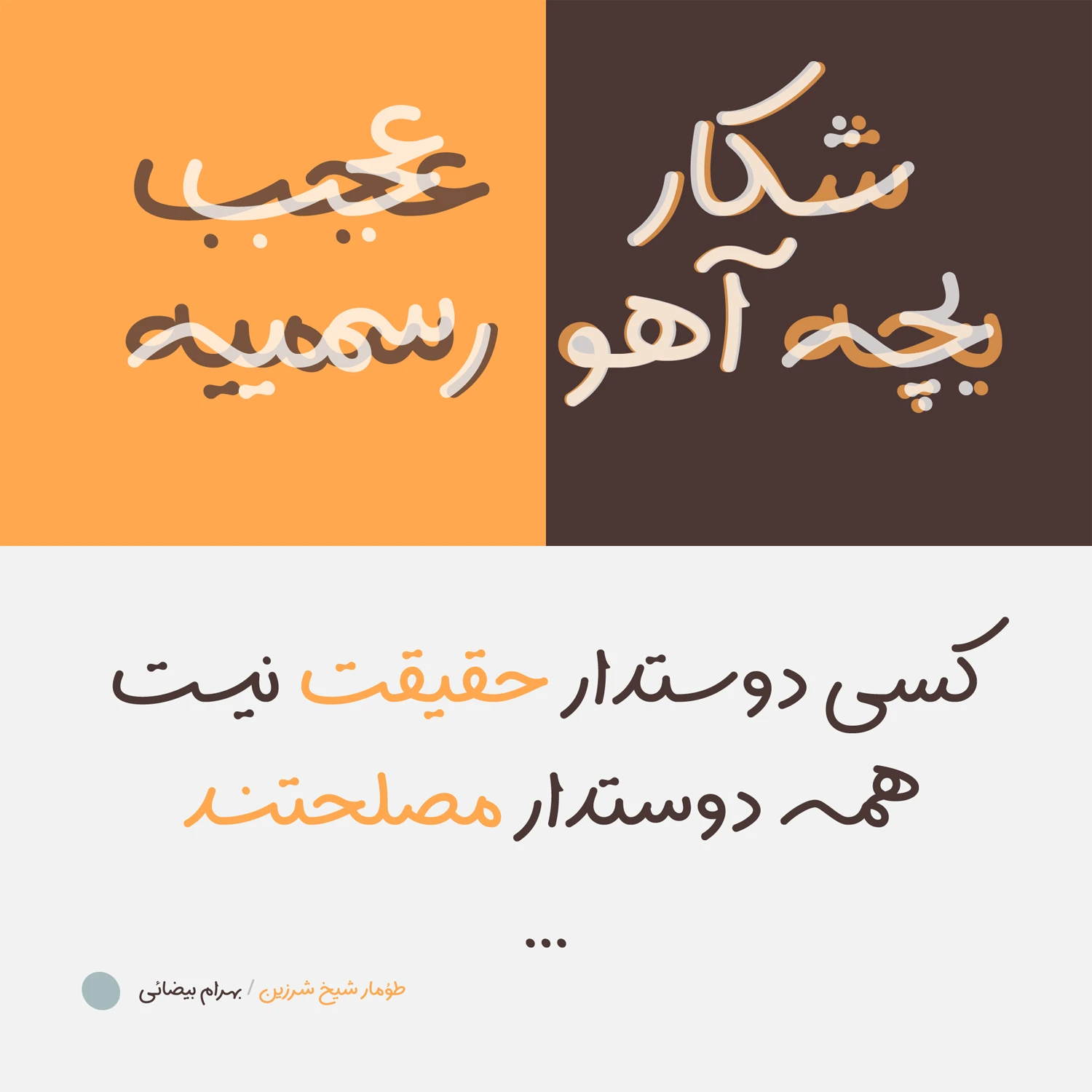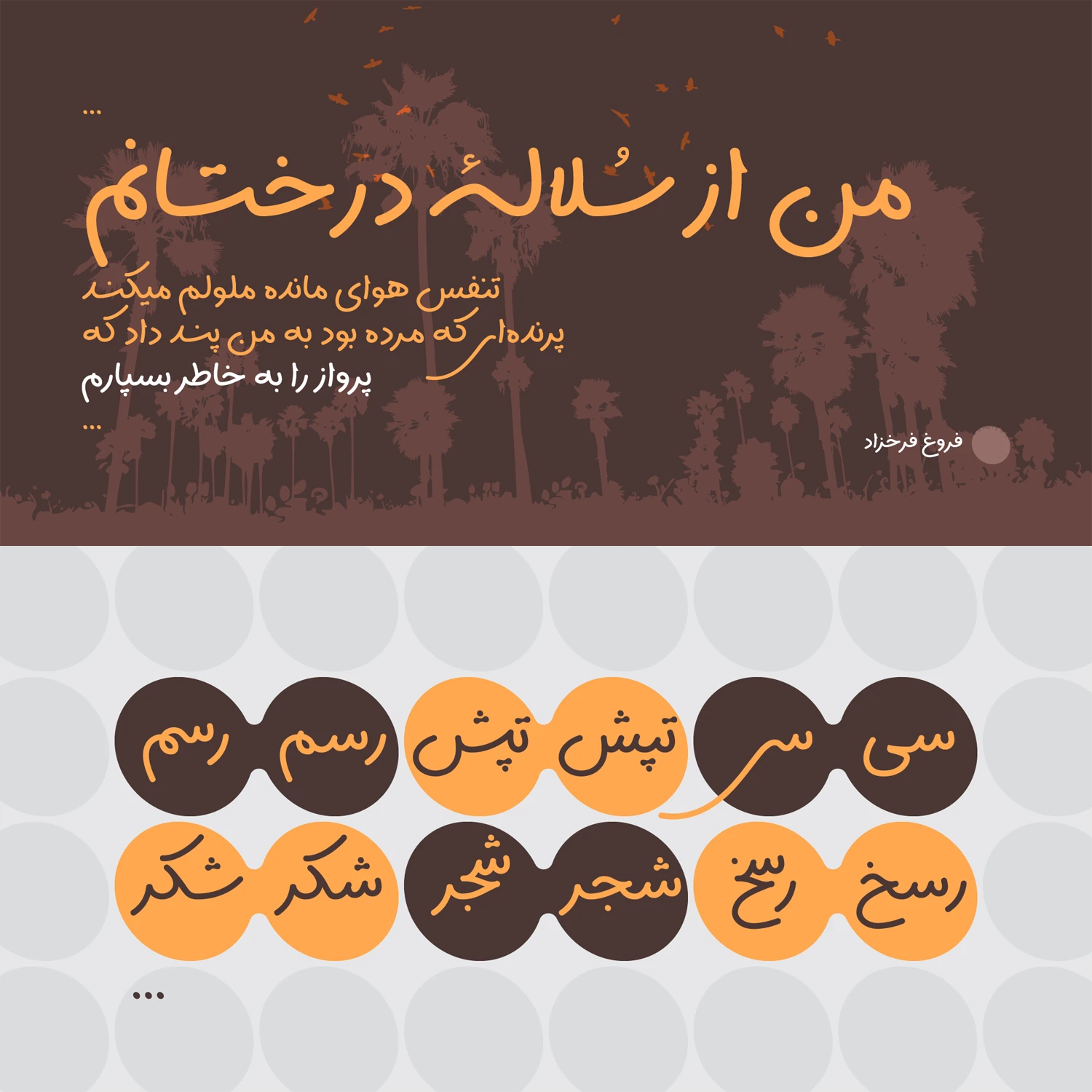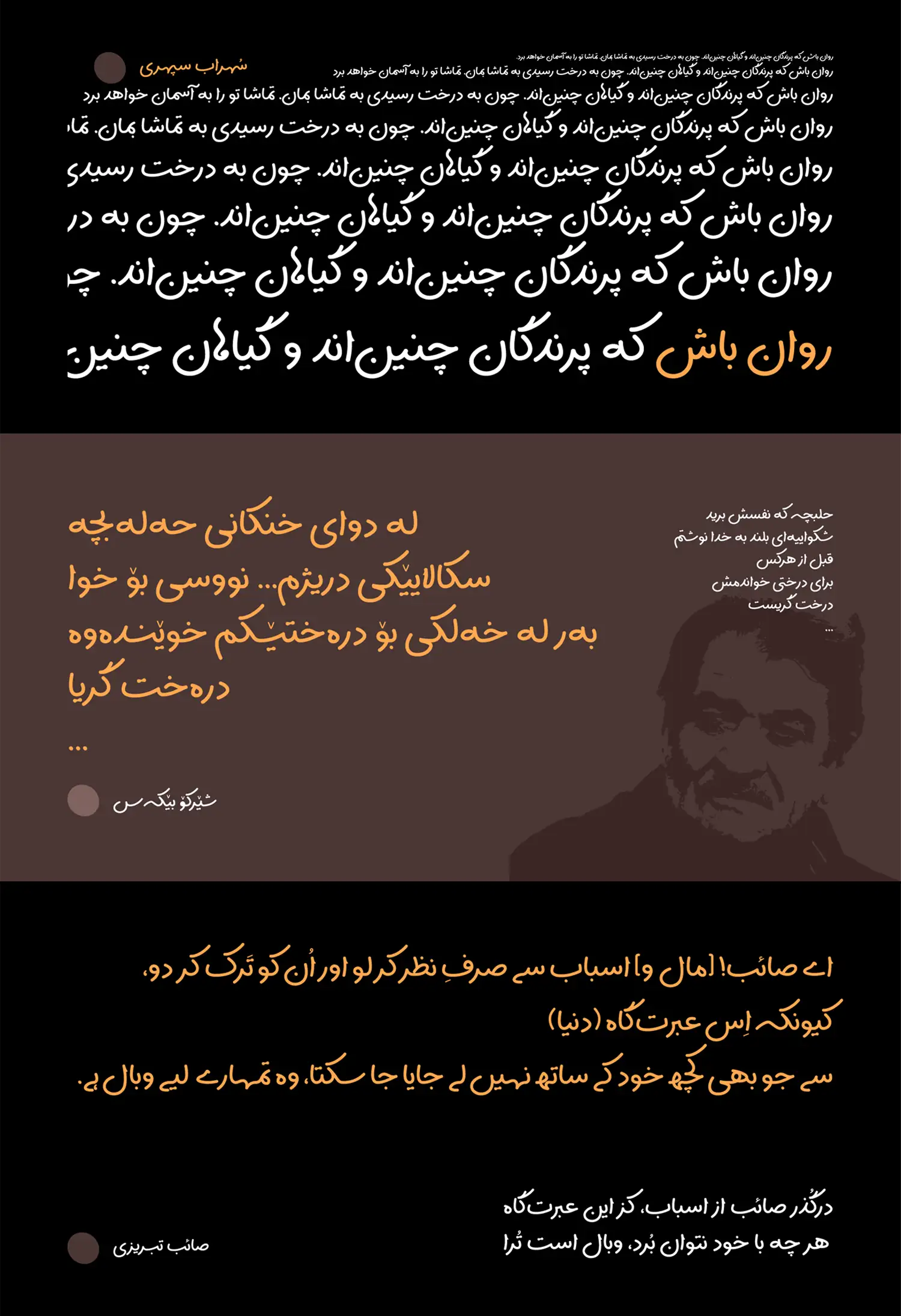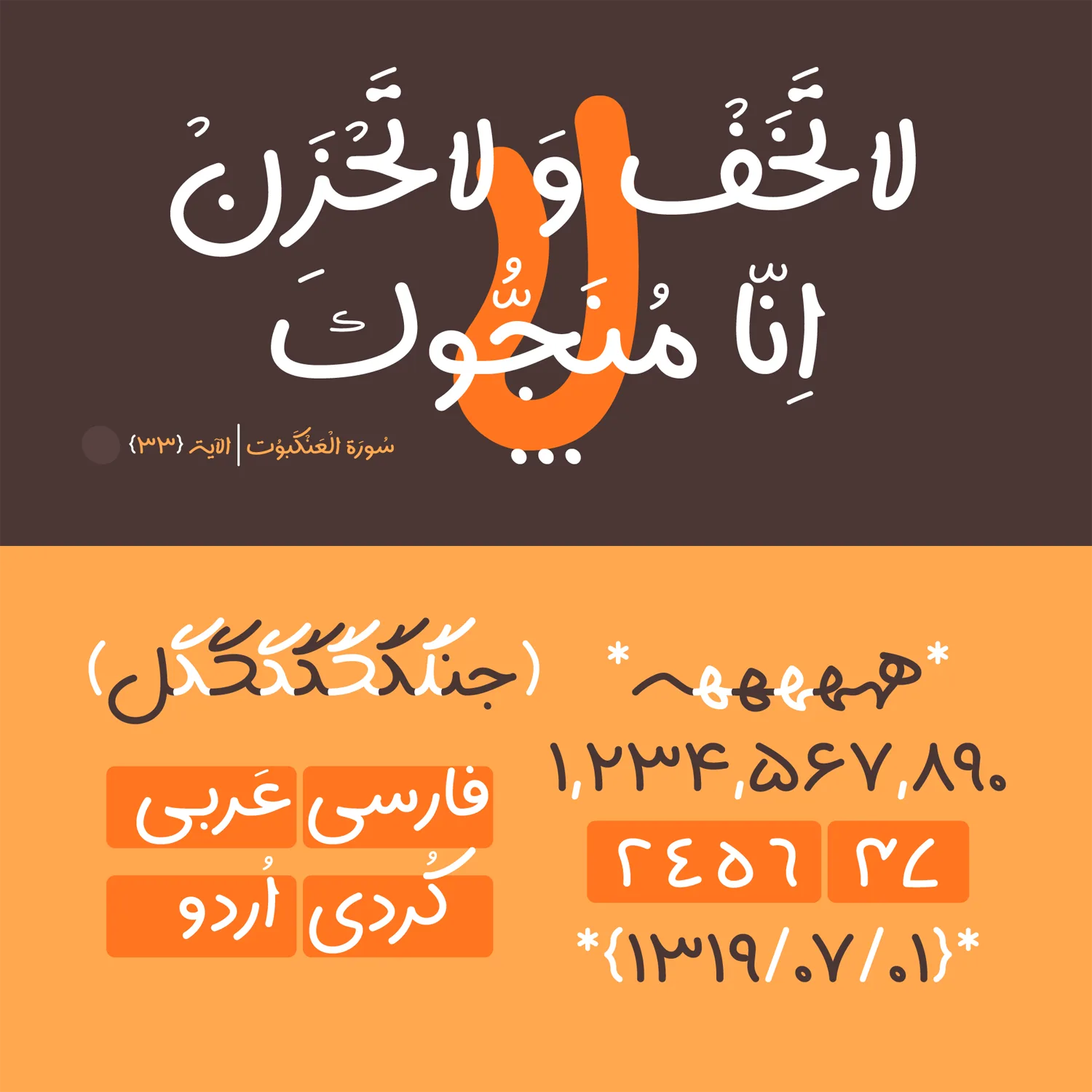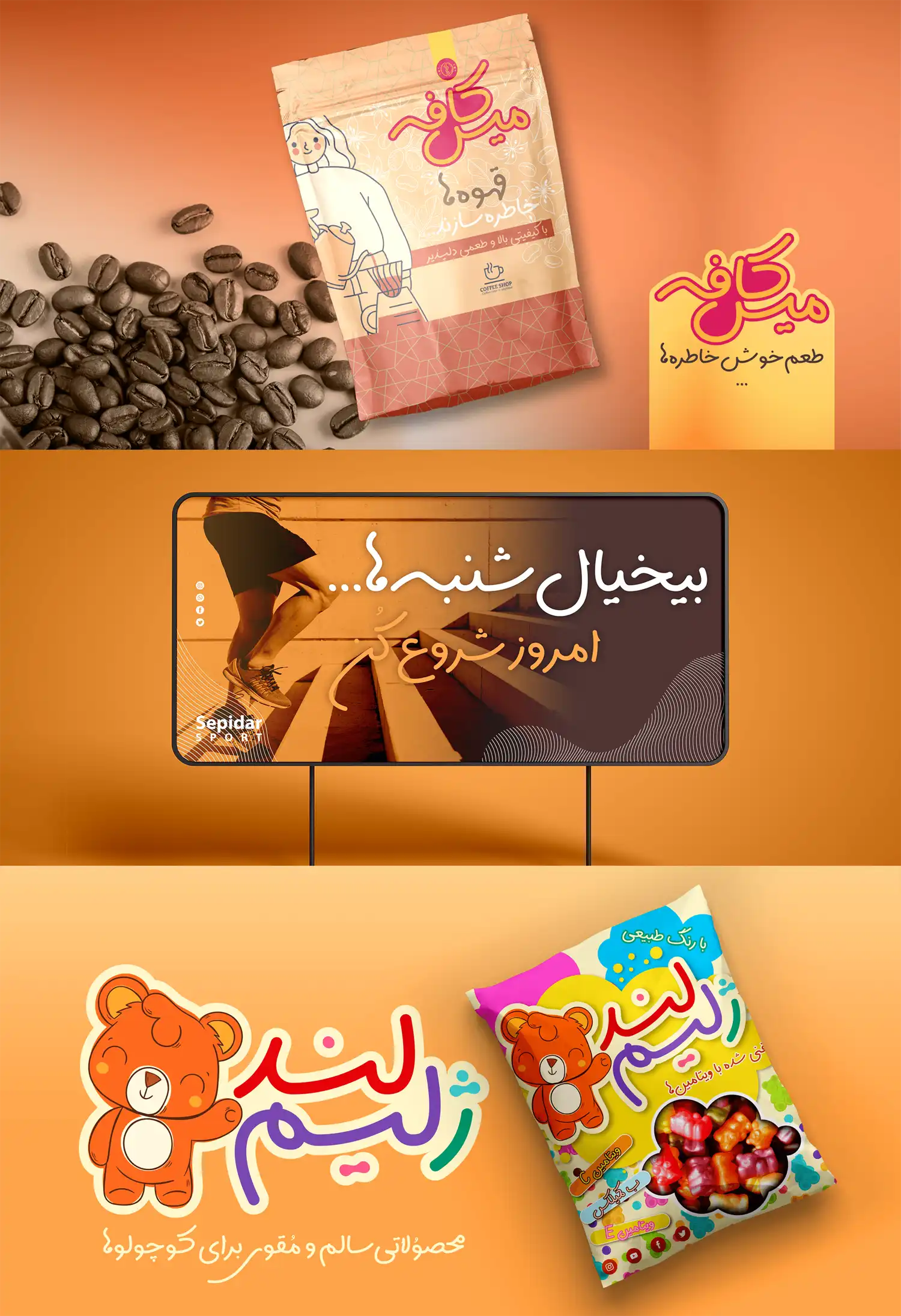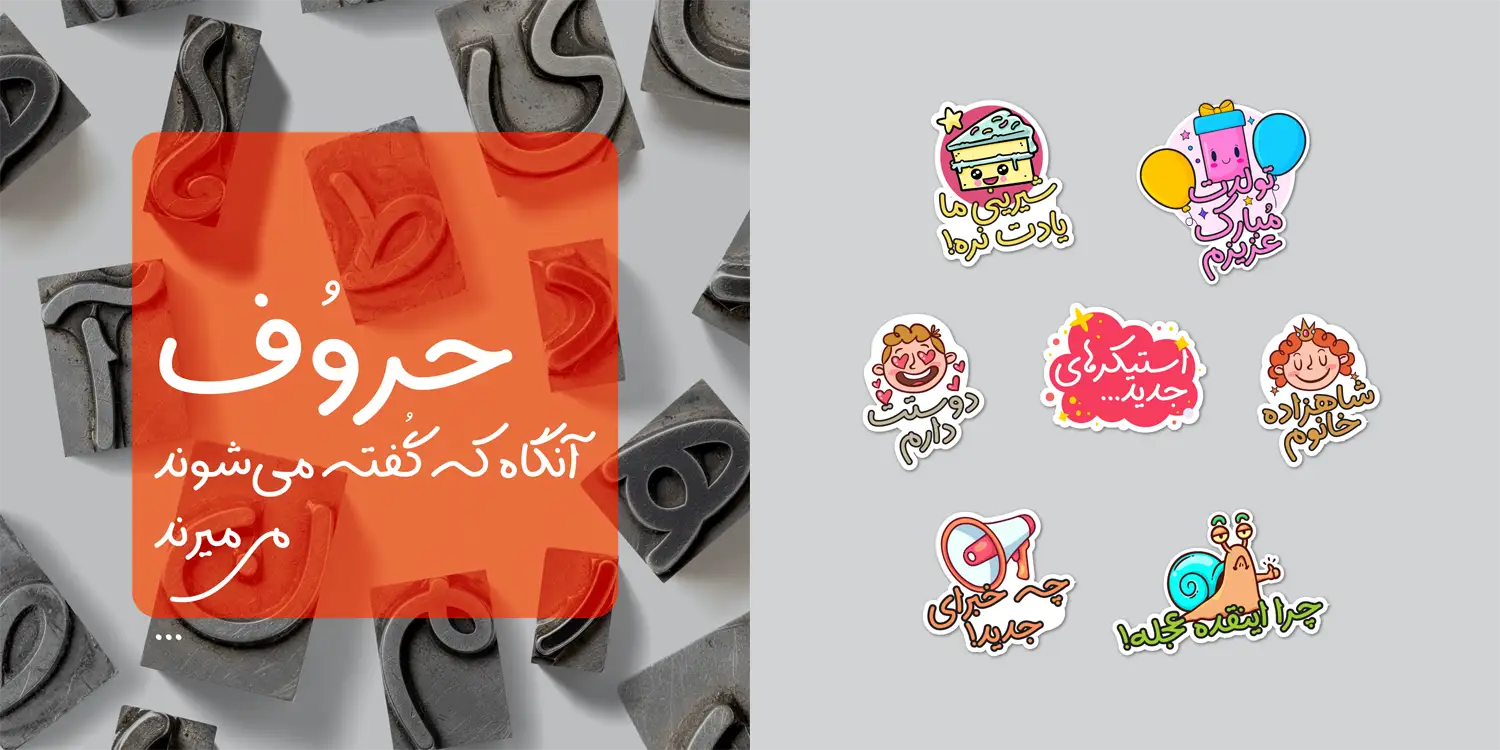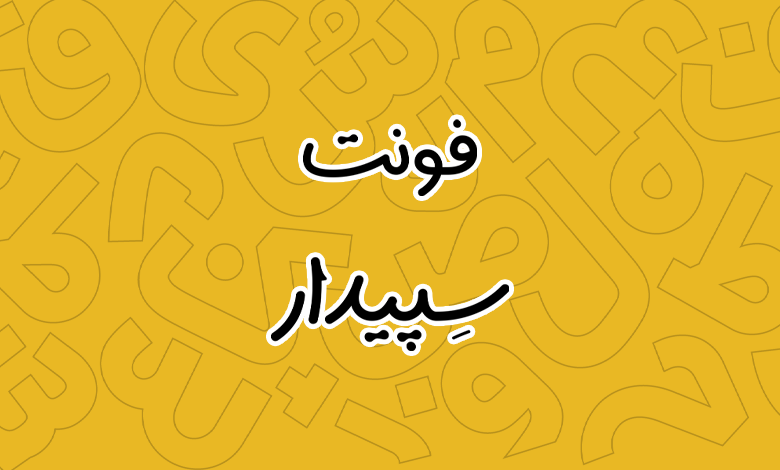
فونت سپیدار (Sepidar)
ایده شکلگیری فونت سپیدار از یک فونت دستخط شخصی شروع شد که حالا به فونت دیجیتال تبدیل شده است. این فونت که دارای شخصیتی سیال و پویا است، برای استفاده در متونی که جنبه تبلیغاتی و نمایشی دارند کاربرد دارد. با اینکه از یک وزن متوسط پشتیبانی میکند، اما ساختار نمایشی آن با تنوع لیگچرها و حروف جایگزین بهطوری است که آن را به انتخابی مناسب برای انواع متون کوتاه، متوسط و نسبتا بلند تبدیل کرده است.
از فونت Sepidar میتوانید در موضوعات مختلفی استفاده کنید. از طراحی جلد کتب و مجلات گرفته تا طراحی استیکر برای شبکههای اجتماعی، ساخت پوسترهای خلاقانه، بنرهای تبلیغاتی و حتی بستهبندی محصولات که جذابیت فوقالعاده این فونت باعث جلب توجه بیشتر خواهد شد.
طراحی فونت سپیدار توسط حسین مبینی پور انجام گرفته که جزو اولین تجربههای وی در زمینه تایپوگرافی است. توسعه و تبدیل آن به فونت نیز توسط شهرزاد اکبری انجام گرفته که پیش از این سابقه طولانی در همکاری با طراحان مختلف برای ورود فونتهای مختلف به فضای دیجیتال فارسی داشته است. در ادامه بیشتر با این فونت فارسی آشنا میشویم.
برجستهترین ویژگی سپیدار، ایده و پایه طراحی آن است. طراح، این فونت را بر مبنای «کلام» و فرم بیان ادای کلمات خلق کرده است. این رویکرد باعث شده تا سپیدار صرفا یک ابزار برای خواندن نباشد، بلکه خودش راوی یک حس باشد.
فرم حروف در فونت سپیدار، بر پایه خطوط اصیل ایرانی و عربی شکل گرفته است؛ اما با رویکردی کاملا مدرن و گرافیکی که ساختاری زیبا به آن بخشیده است. این فونت موفق شده تضادی جذاب را در خود حل کند، در نگاه اول شمایلی آرام و منعطف دارد، اما در باطن، حسی هیجانی، پرنشاط و فعال را به بیننده القا میکند.
سپیدار برخلاف بسیاری از فونتها که حروف به صورت خطکشگذاریشده روی یک خط صاف قرار میگیرند، چسبیده به خط مبنا نیست. استفاده هوشمندانه از قوسها و انحناها به کلمات شخصیتی پرتحرک، سیال و در عین حال منسجم و یکپارچه بخشیده است.
نقطه قوت اصلی سپیدار در ابزارهایی است که در اختیار طراح گرافیک قرار میدهد. این فونت دارای مجموعهای غنی از لیگچرها و ترکیبات جایگزین است. این ویژگی به کاربر اجازه میدهد تا با دست باز، فرم حروف را تغییر داده و چیدمانی شخصیسازیشده و جذاب از کلمات خلق کند. در واقع، سپیدار یک «ابزار جامع تایپوگرافی» است، نه فقط یک فونت ساده.
با وجود فرمهای نمایشی و انحناهای پیچیده و پشتیبانی فقط از یک وزن متوسط Medium، ساختار مهندسیشدهی سپیدار تضمین میکند که این فونت در هر سایز و ابعادی (از بیلبوردهای بزرگ تا صفحات وب) وضوح و خوانایی خود را از دست ندهد.
فونت سپیدار از زبانهای فارسی، عربی، اُردو، کوردی و لکی پشتیبانی کاملی دارد. این فونت دارای مجموعهای کامل از اعراب، علائم و کلمات مختص این زبانهاست. در نسخه فارسی نسخه مخصوص اعداد فارسی هک شده در کنار نسخه دیگری که فاقد اعداد انگلیسی و عربی هستند نیز قرار داده شده است.
این فونت همچنین در بخش اعداد نیز دارای نقاط قوتی است. از جمله اینکه از ویژگی MonoSpace برای هم تراز کردن عمودی اعداد پشتیبانی میکند. این ویژگی اجازه میدهد در مواردی همچون جداول و قیمتگذاریها ساختاری منظم به اعداد خود بدهید که روی جلب توجه مخاطب نیز تاثیر خواهد گذاشت.
کاربردهای فونت سپیدار
فونت سپیدار شاید از نظر ظاهری یک فونت دستنویس باشد، اما ذاتا شخصیتی نمایشی دارد. این یعنی برای متنهای طولانی و ریز (Body Text) طراحی نشده است، بلکه برای درخشش در ابعاد بزرگ ساخته شده است. نرمی و انعطاف این فونت، آن را به انتخابی بیرقیب برای موارد زیر تبدیل میکند:
- شعارهای تبلیغاتی و کمپینها: جایی که لحن برند باید پرانرژی و متفاوت به نظر برسد.
- تیترها و عنوانها (Headlines): در طراحی پوستر، بیلبورد و مجلات.
- طراحی بستهبندی و لوگوتایپ: کلماتی که مستلزم «جور دیگر دیده شدن» هستند و باید در ذهن مخاطب حک شوند.
- طراحی پوستر و کارهای گرافیکی: موضوعاتی فانتزی، کودکانه و داستانی که استفاده از این فونت لحنی گرم و صمیمی به محتوای شما خواهد داد.
فونت سپیدار یک تایپفیس نمایشیِ پرانرژی، مدرن و به شدت انعطافپذیر است. اگر یک طراح گرافیک هستید که برای پروژههای تبلیغاتی، طراحی پوستر یا تیترهای جذاب به دنبال فونتی میگردید که دست شما را برای ترکیببندیهای خلاقانه باز بگذارد، فونت سپیدار با مجموعهی کامل لیگچرهایش، انتخابی عالی برای شماست.